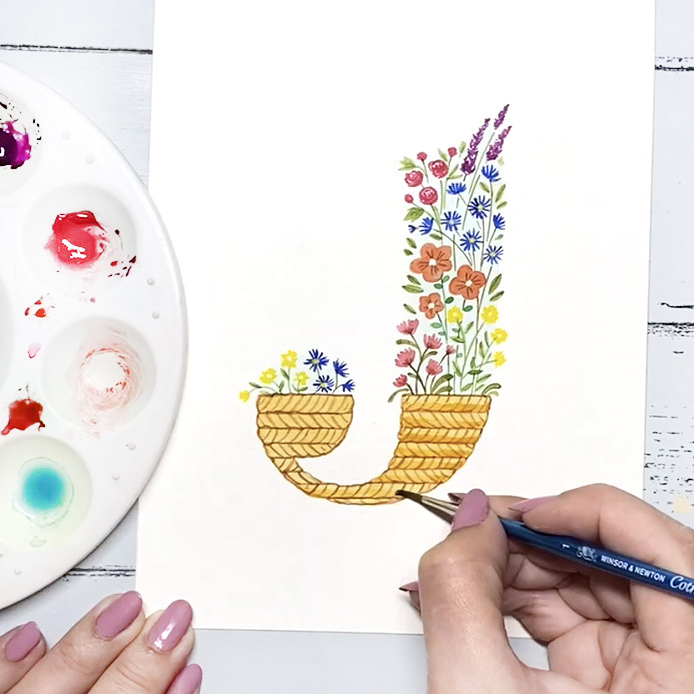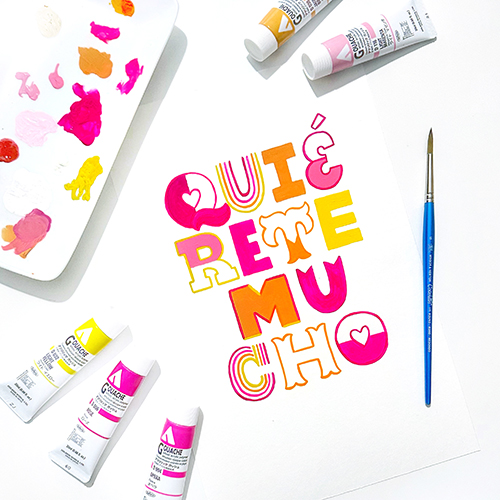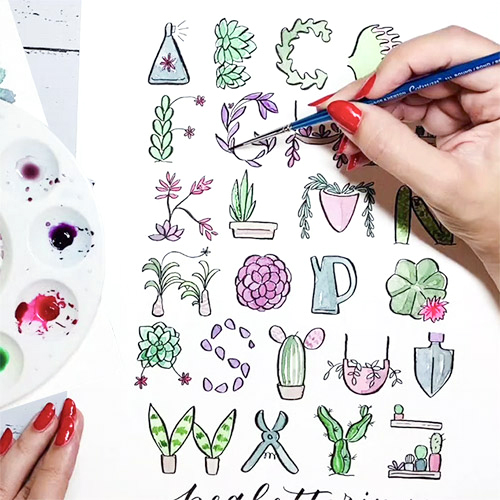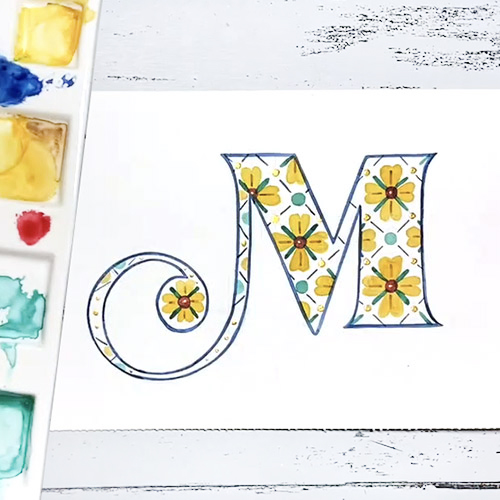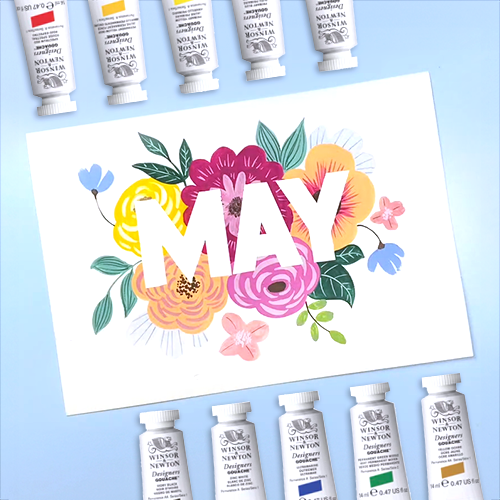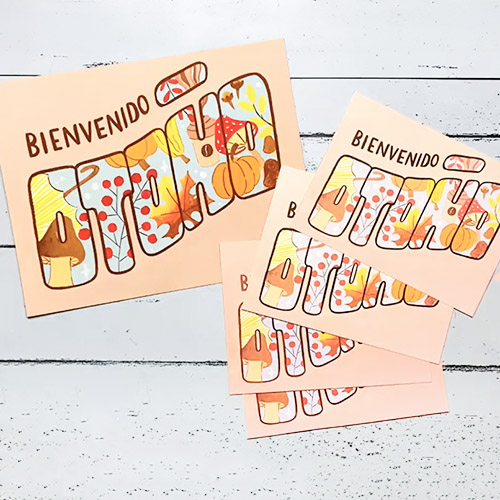
Aquí tienes los proyectos que aprenderás a hacer
en estas clases:
Alfabeto botánico
Crea un alfabeto original utilizando ilustraciones. Puedes recrear el alfabeto botánico de ejemplo o hacer el tuyo propio con la temática que tú elijas. Una vez terminado, utilízalo para crear palabras y desatar todo su potencial.
Iniciales de acuarela
Para regalar, para decorar o simplemente porque son muy divertidas de dibujar. Las láminas de iniciales son un proyecto muy versátil y en estas clases aprenderás diferentes estilos que se adaptan a todos los gustos.
Fondos con gouache
El gouache o témpera es un material que permite crear trazos opacos y semitransparentes, y lo utilizaremos en muchos proyectos de este curso. Además de letras, aprenderás a utilizarlo en diferentes tipos de ilustraciones.
Postales ilustradas
La combinación de lettering e ilustración es perfecta para un montón de proyectos. Uno de ellos son las postales, y con estas clases descubrirás como crear el diseño perfecto con gouache y tus colores preferidos.
Lettering con gouache
Además de crear láminas de lettering con gouache y acuarela, también aprenderás a fotografíar y editar el resultado, para poder compartir tus creaciones en redes sociales con imágenes que pongan en valor todo tu trabajo.
Iniciales ilustradas
Aprende a mezclar acuarelas y gouache para aprovechar las mejores características de cada técnica. Aplica todo lo aprendido a proyectos cortos pero llamativos, que puedes utilizar en un montón de ocasiones distintas.
Por qué aprender lettering es una buena idea
El lettering es una habilidad artística que no solo despierta tu creatividad, sino que también puede convertirse en una valiosa herramienta profesional.
Tanto si lo practicas como hobby o quieres explorar nuevas oportunidades laborales, aprender lettering te abre las puertas a un sinfín de posibilidades. Puedes aplicarlo en diseño gráfico, creación de logotipos, papelería personalizada, murales, y mucho más. Además, lo genial del lettering es que no estás limitado a un solo tipo de material: puedes experimentar con rotuladores, pinceles, acuarelas, tinta, e incluso herramientas digitales.